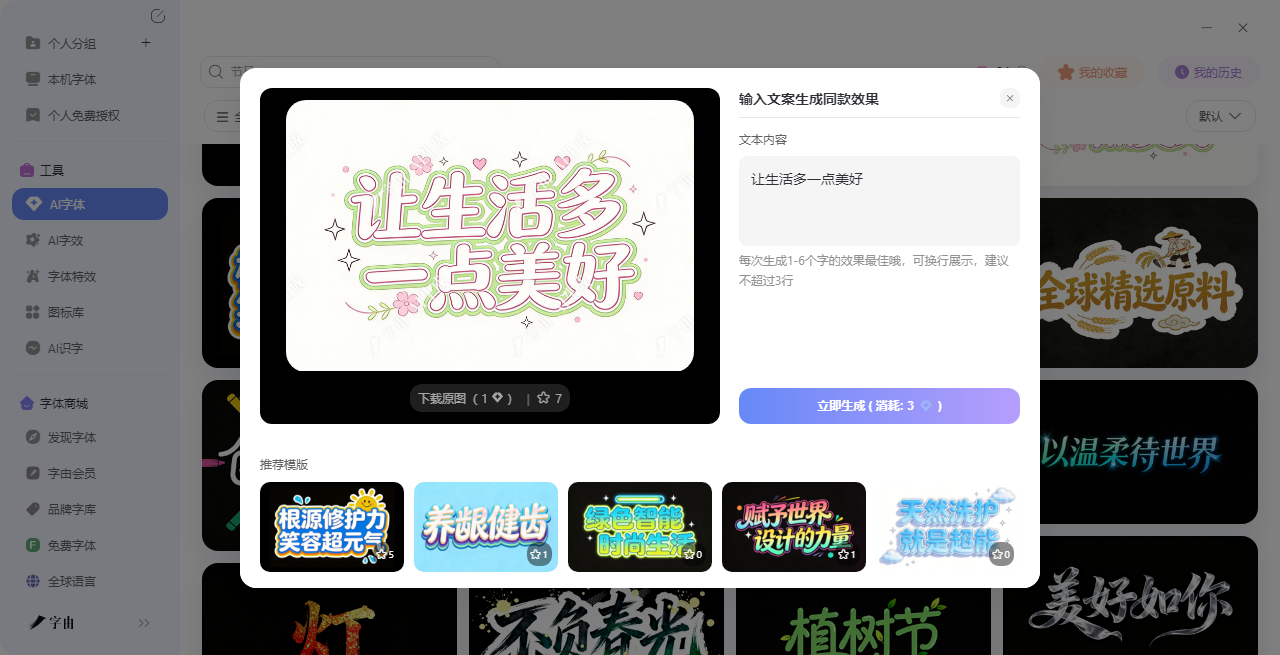
在线实时字体生成工具,所见即所得,设计字体不再困难!
做设计的时候,你有没有过这样的体验:灵感来了,想试一款字体,结果要先去网上搜、下载、解压、安装,再重启软件才能看到效果。等你折腾完,灵感早跑没影了。更别说试第二款、第三款,时间就这么一点一点被吃掉。如果有一个工具,能让你在输入文字的同时,实时看到不同字体的效果,你肯定会心动。字由的AI字体功能,就是这样一个在线实时字体生成工具。它把“选字体”这件事,从繁琐的下载安装,变成了简单的点一点、看一看。今天这篇文章我会教大家如何使用字由的AI 字体功能。
1、为什么选择字由AI字体
打开字由客户端,进入AI字体页面,你会看到一个搜索框和密密麻麻的模板预览图。在搜索框里输入你的文案,比如“春日限定”,然后开始浏览模板。鼠标滑过一个模板,预览图里就会立刻用你的文案展示效果。点进去,还能看到更大的预览。这个过程没有任何延迟,你不需要等待下载,不需要纠结“这字体适不适合”,看一眼就知道。
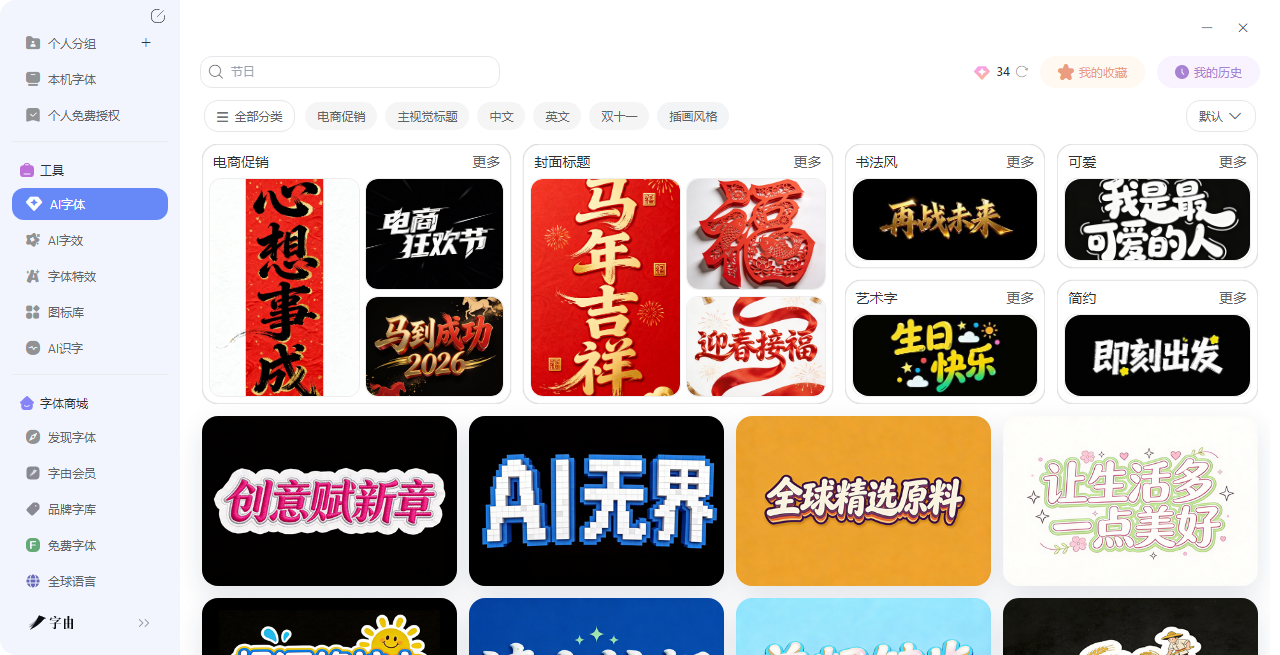
这种感觉,就像你在超市里挑水果,看到喜欢的就拿起来看看,不喜欢的放下就行。没有人催你,也没有试错成本。想试什么风格,就点开对应的模板——想试试复古霓虹?点“午夜电台”。想试试温柔手写?点“春日”。想试试喜庆节日?点“元宵快乐”。
每个模板都是一个完整的字体设计方案,你只需要确认这个方向对不对。这种实时性,最大的价值不是节省那几分钟下载时间,而是保护你的设计思路。灵感是连续的,一旦被打断,可能就再也接不上了。字由让你在灵感最活跃的时候,一口气试完所有可能的方向,然后挑出最对的那个。
2、字由AI字体的“所见即所得”
传统的字体选择,很多时候是“盲选”。你下载一款字体,装上去,看到效果,可能和想象中差很远。因为预览图里的字是别人写的,不是你的文案,也不是你的设计语境。字由的“所见即所得”,是让你用自己的文字,在自己的设计语境里,实时看到效果。
你输入什么,模板就用什么展示。你输入“我们结婚啦”,模板就展示“我们结婚啦”;你输入“开业大吉”,模板就展示“开业大吉”。不同字重、不同风格、不同配色,一目了然。
更好的是,字由的AI字体模板还支持透明背景导出。你看到的效果,就是最终能拿到图。选中一个模板,点“生成”,几十秒后就能下载PNG。背景可以透明,也可以保留。拖进PS、剪映、Canva里,直接就能用。
3、字由AI字体的丰富性
字由的AI字体模板库,远比你想象的丰富。它不是只有“字体”这个分类,而是按场景、风格、用途做了细致的划分。
- 按场景:电商促销、主视觉标题、海报、请柬、包装、短视频……
- 按风格:国潮风、科技感、可爱风、手写风、复古霓虹、简约现代……
- 按用途:节日、活动、品牌、文案、封面、字幕……
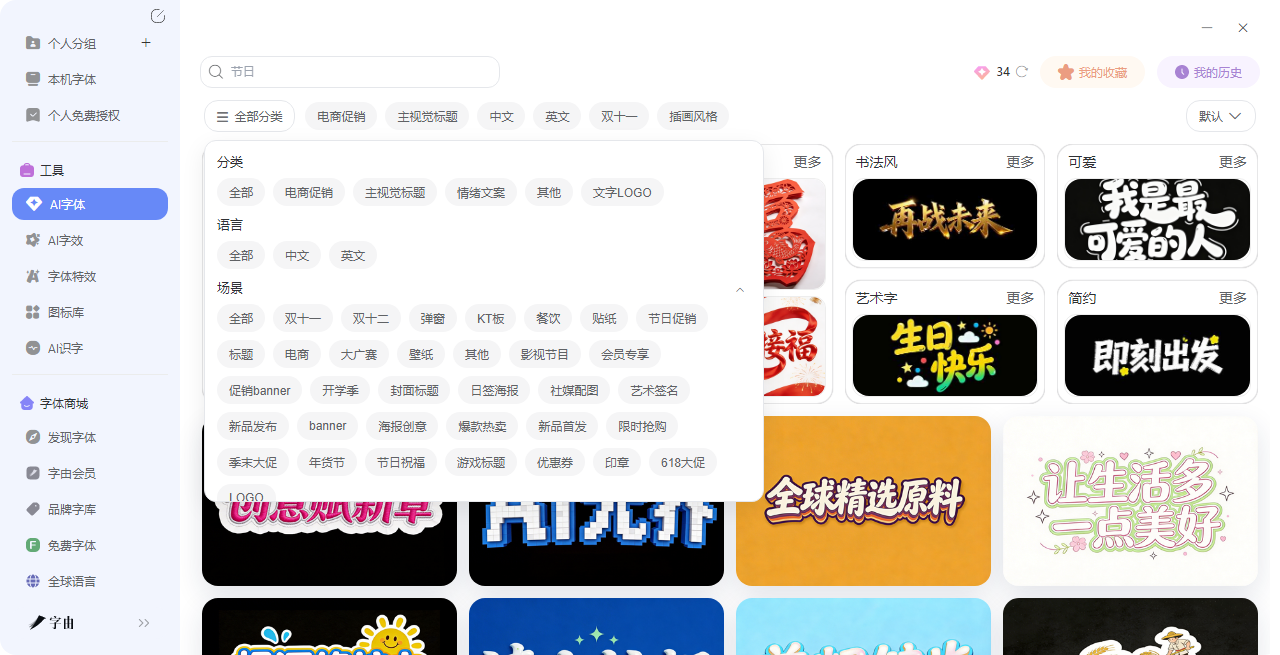
每个模板都是一个完整的设计方案,不是单纯的字体,而是带配色、带效果、带氛围的“字体设计”。你不需要自己调参数,选一个喜欢的,改文字就行。
比如你想做一个美食视频的封面,可以搜“美食”,找到“深夜食堂”模板,把文字改成“今天吃啥”,生成一张有食欲的标题字。你想做一个旅行vlog,可以搜“旅行”,找到“在路上”模板,把文字改成“出发吧”,生成一张有自由感的开场字。你想做一个婚礼请柬,可以搜“婚礼”。
这样其实就把挑选字体的成本压缩到了最低,并且产出的质量还不差,这简直最好的在线实时字体生成工具。而且模板库还在不断更新,每隔一段时间就会新增一批新风格。
4、字由AI字体的便捷性
选好字体只是第一步,怎么用到设计里才是关键。字由在这方面做得特别贴心。
- 一键生成:选好模板,点“生成”,等几十秒,就能拿到高清PNG。不需要自己抠图,不需要调色,不需要加效果,全部打包给你。
- 透明背景:生成时可以选透明背景,直接拖进设计软件里用。
- 多格式支持:除了PNG,还支持导出带背景的图片,方便直接用在社交媒体。
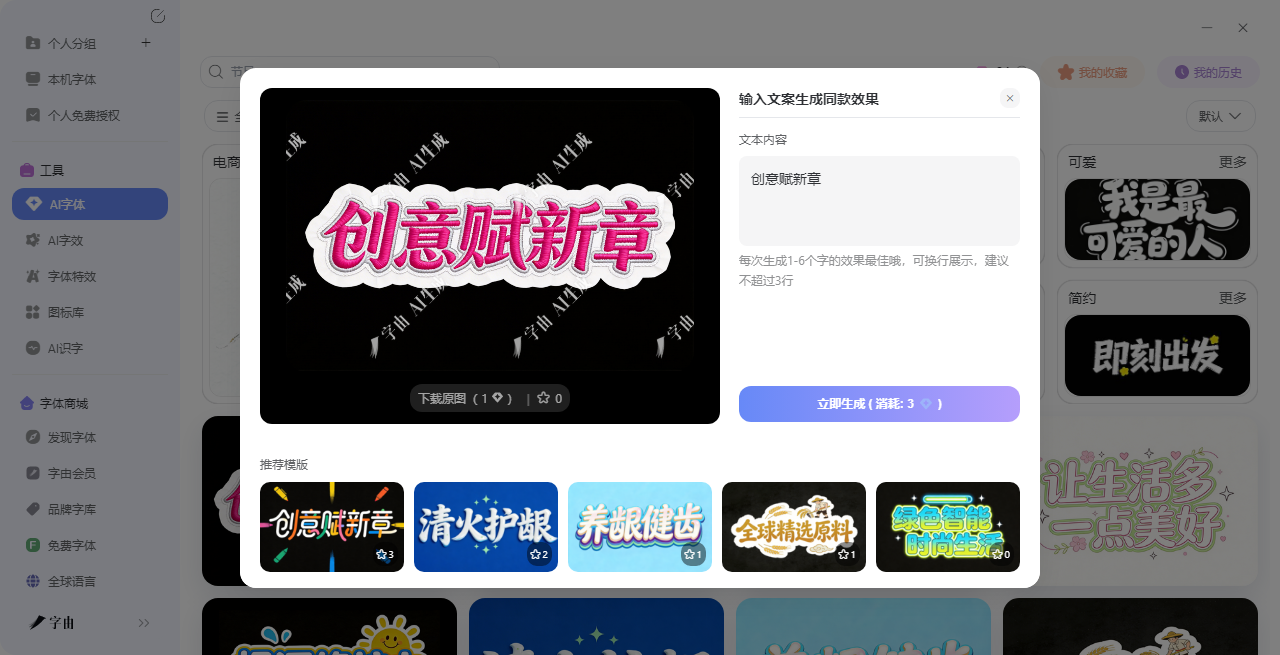
- 一键应用字体:如果你用的是PS、AI、Figma这些设计软件,字由的客户端还能直接一键应用字体。选中文字图层,在字由点一下,文字实时切换。不用下载,不用安装,不用重启。
这也是我喜欢用字由AI工具的理由,十分便捷。
这些AI工具和AI字体配合使用,几乎能覆盖设计过程中所有和文字相关的需求。从找灵感,到选字体,再到加特效,最后出图,一步到位。